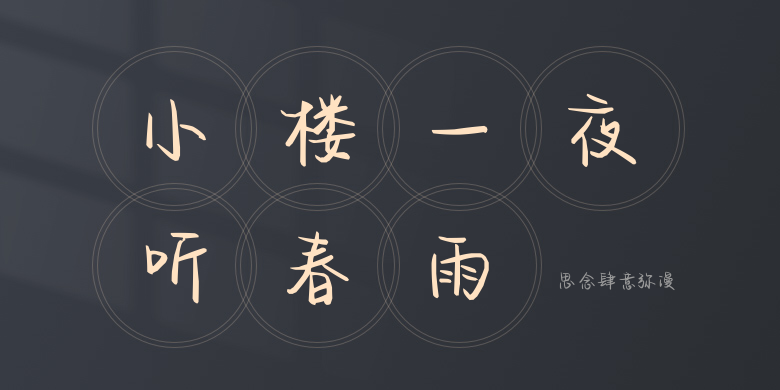
思念肆意弥漫
思念肆意弥漫,这款字体结构工整、笔画清晰,兼顾美观与易读性,适用于标题、正文、海报、包装、LOGO 等多种场景。字形优雅稳定,风格百搭耐看,适配日常排版与创意设计,让文字呈现更舒适、更具质感。思念肆意弥漫一笔一画,皆是细节,以均衡的比例、流畅的线条打造舒适视觉体验,字形端正大气,风格简约现代。无论是商业设计、品牌宣传还是日常排版,都能轻松驾驭,让文字更有格调与力量。思念肆意弥漫字体下载。